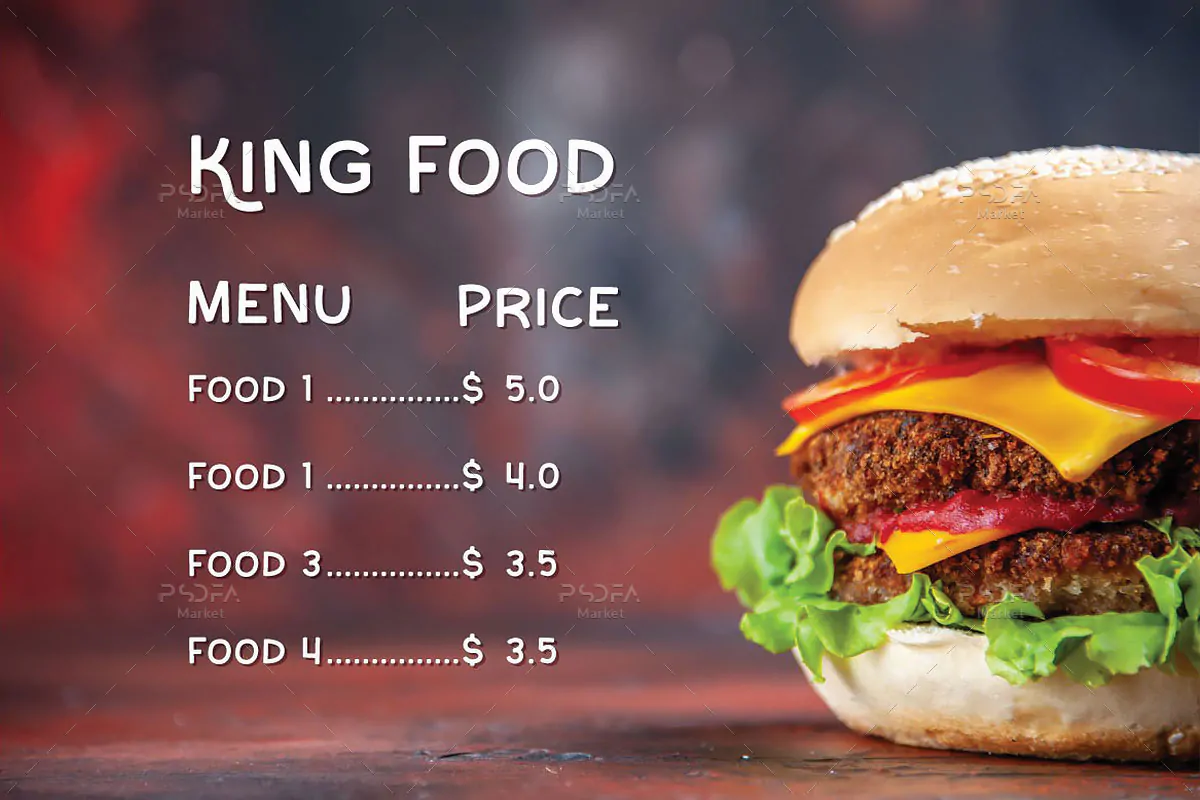
فونت کمیک Hamburges
فونت کمیک انگلیسی
فونت کمیک Hamburges یک قلم سنس سریف انگلیسی است که مناسب جهت استفاده در طرح و پروژههای گرافیکی مختلف میباشد. فونت Hamburges با وزن معمولی طراحی شده است که میتوانید از آن در طراحی انواع پوستر، بروشور، تراکت، بنر، منوی غذایی و … ویژه رستوران و فست فود استفاده کنید.